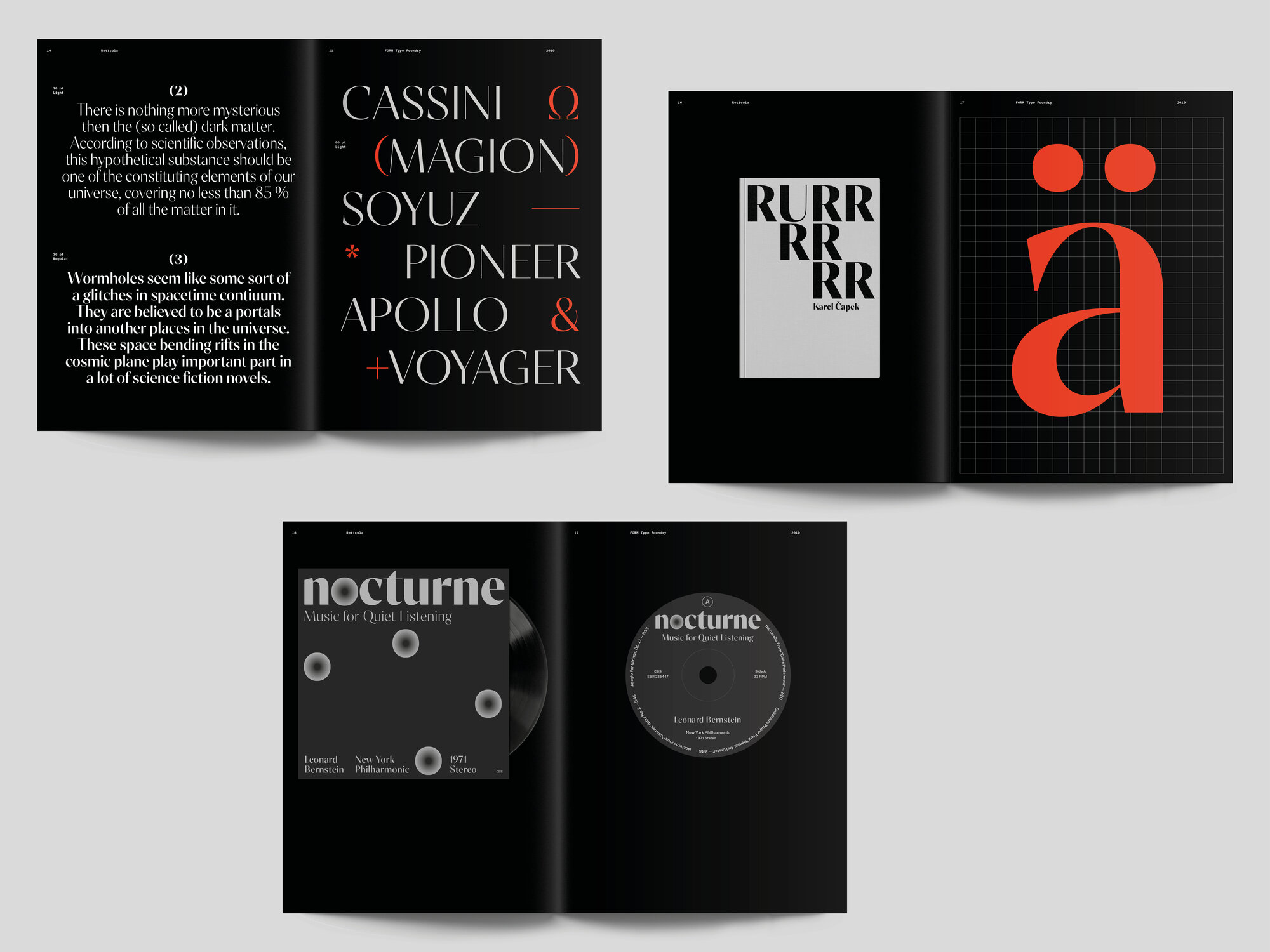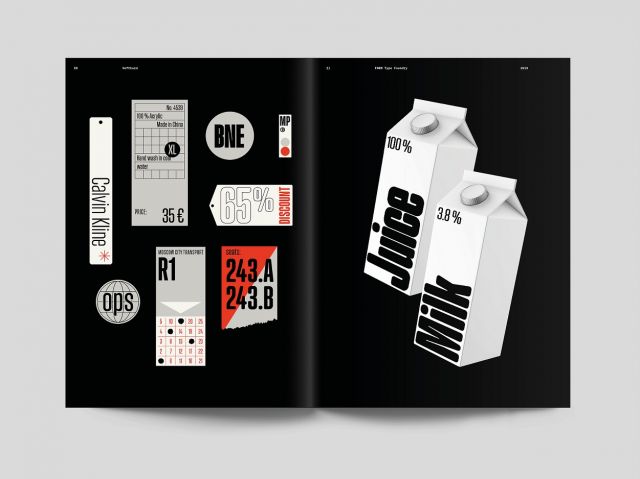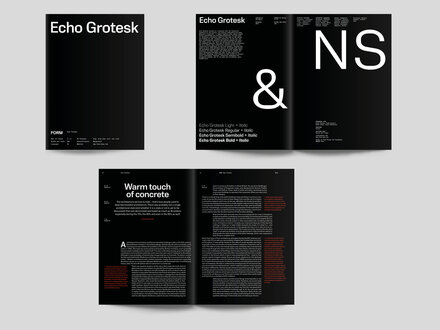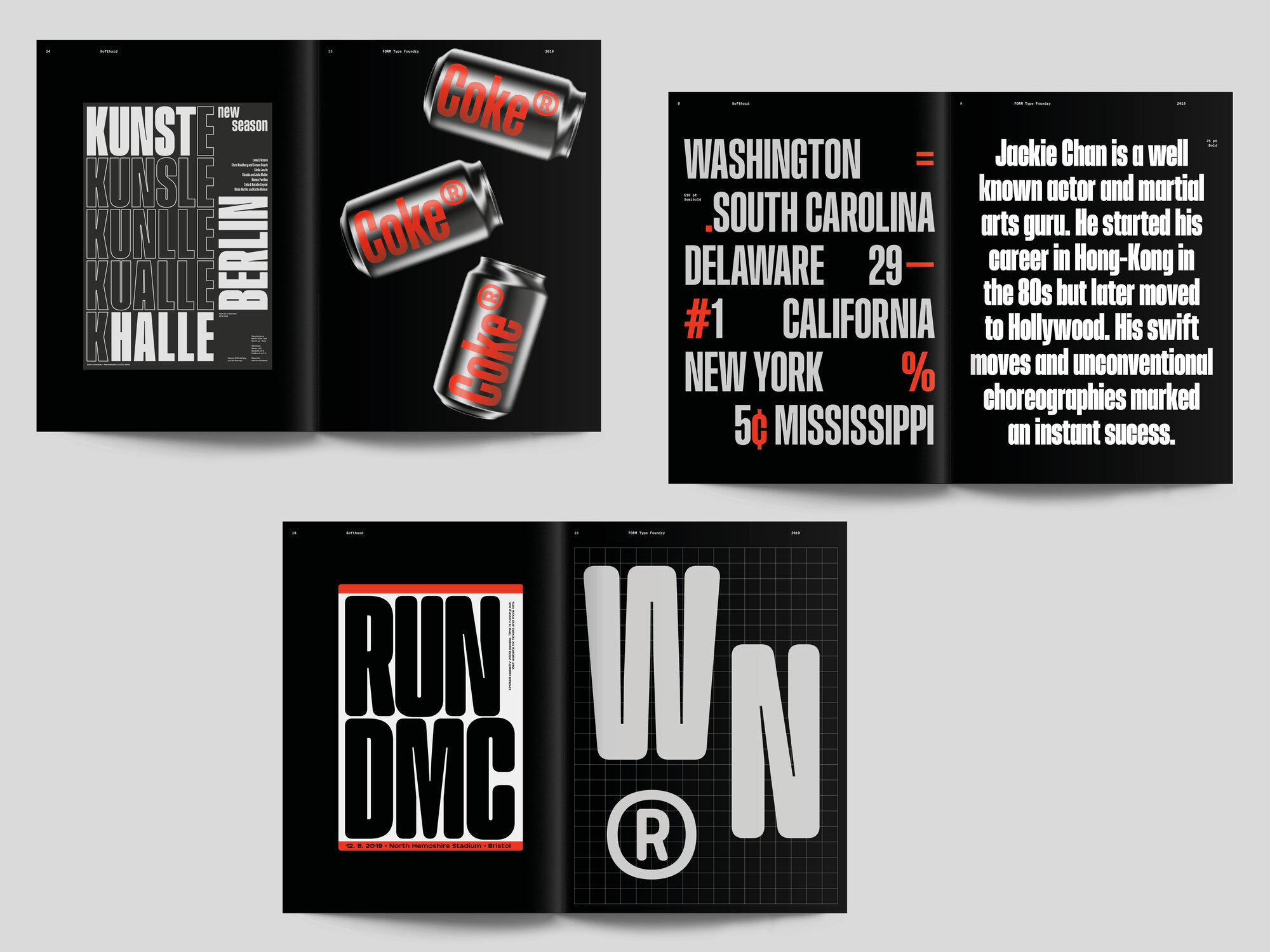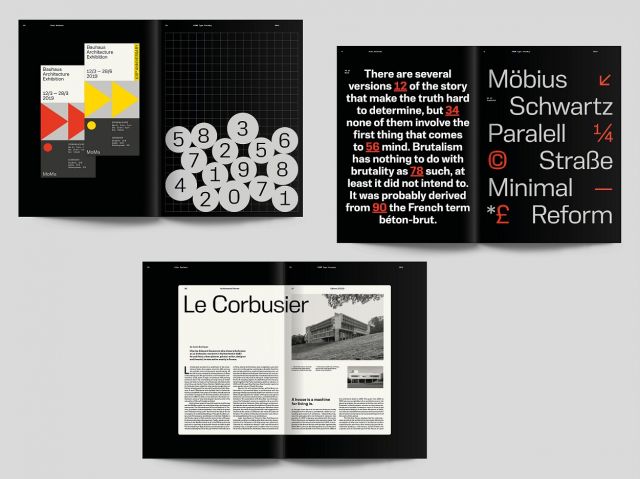
Absolvent Ateliéru tvorby písma a typografie UMPRUM Jan Buble je novým nositelem Národní ceny za studentský design *GRAND. Oceněn byl za svou diplomovou práci, koncept nové české písmolijny Form.
Mezinárodní porota hodnotila jeho práci následně: „Série pěti abeced je více než dostatečný základ nové písmolijny. Rozsáhlý projekt představuje nejen balík profesionálně zpracovaných písem, ale i jejich funkční základnu v podobě uživatelsky přívětivého webu. Nové bezserifové abecedy nepřináší revoluci nebo módní výstřelky – naopak, představují výběr široce využitelných stylů pro běžnou sazbu i výrazné titulky, které obstojí i za deset, dvacet let. Dospělá práce s citem pro detail a pokorou vůči čtenáři, je zaslouženě na piedestalu mezi nejlepšími pracemi".
Písmolijnu Form je možné si prohlédnout na výstavě Nový (z)boží!, která představuje oceněné práce. K vidění je v kreativním prostoru DEPO2015 v Plzni, ale byla zároveň digitalizována: https://app.cloudpano.com/tours/caLuD8AFPf nebo Nový (z)boží! 2020 (indihu.cz).